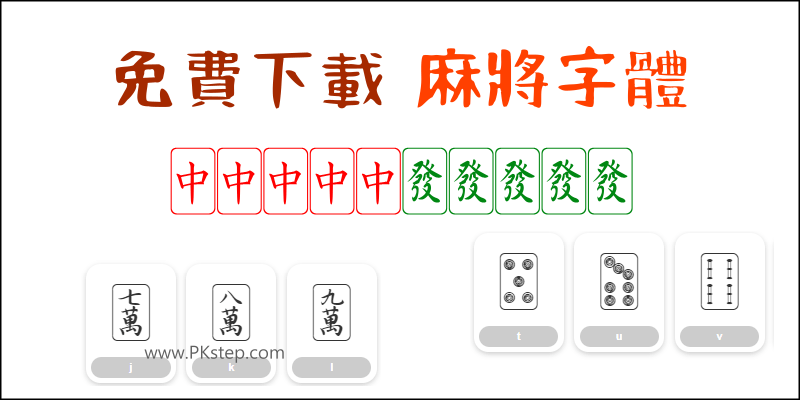
怎麼在電腦上顯示麻將的符號?推薦超酷的Mahjong麻將字體,免費下載與安裝!麻將也可以變成電腦中安裝的字型,在電腦顯示中、發、白、五條、一萬、三筒、三條、八萬等圖案🀄🀄🀄🀄🀄,運用在海報中或圖片中的文子。
電腦麻將字體 說明
步驟2:打法是用鍵盤切換到「英文輸入法」輸入abcd。
步驟3:會發現這些麻將的慣性:
小寫asdfghj….這樣過去是一萬兩萬三萬…
小寫zxcvbnm….這樣過去是一條兩條三條…
小寫123456…這樣過去是東南西發白板發中和骰子。
步驟4:大寫以此類推ABCD,會顯示橫的麻將。